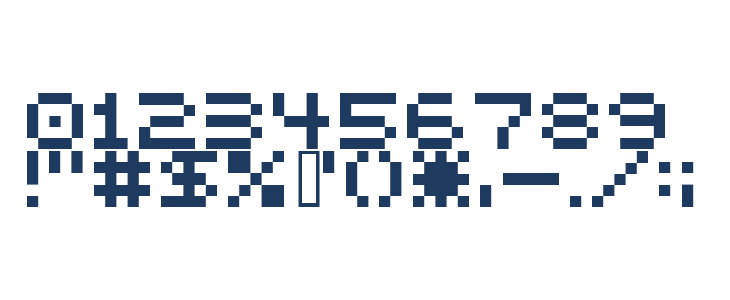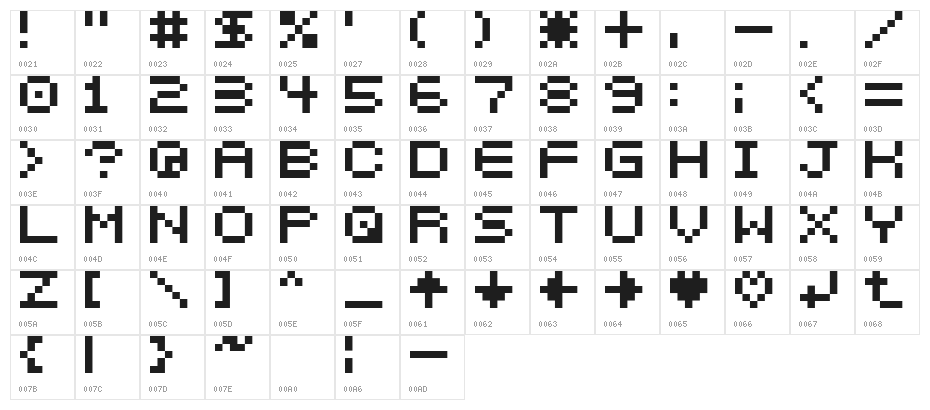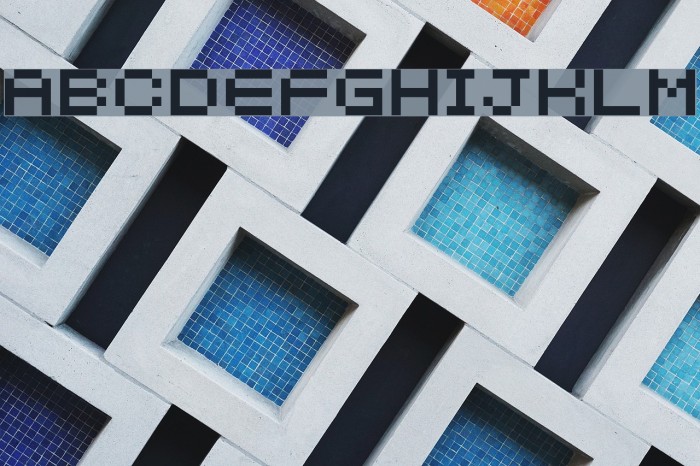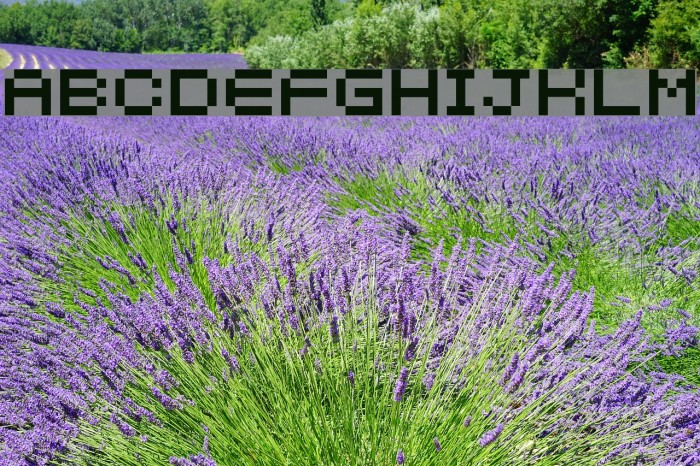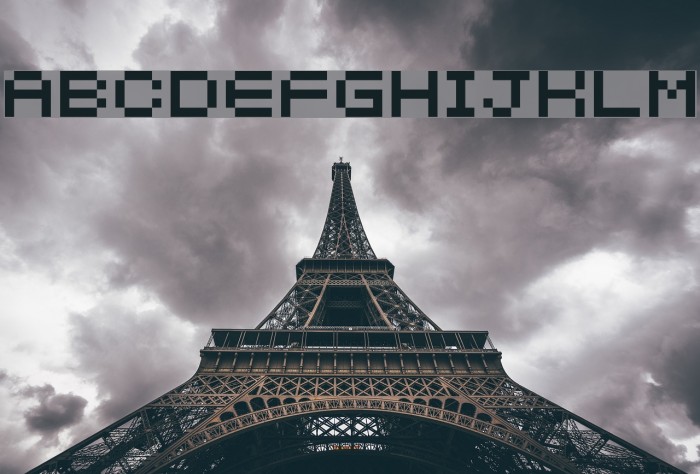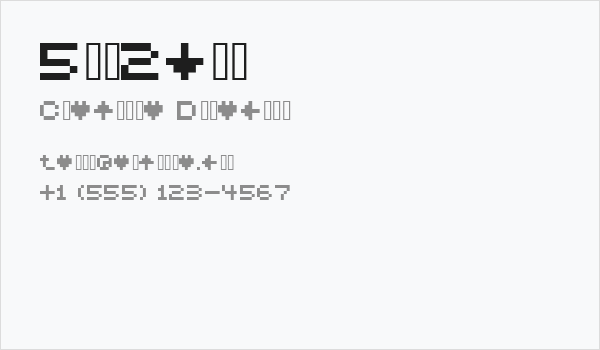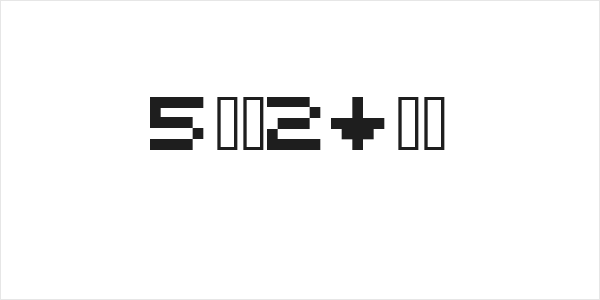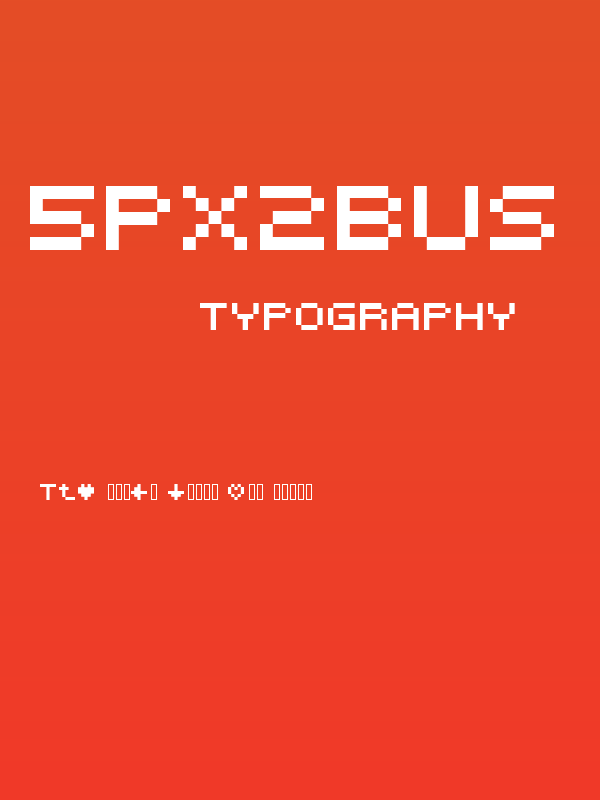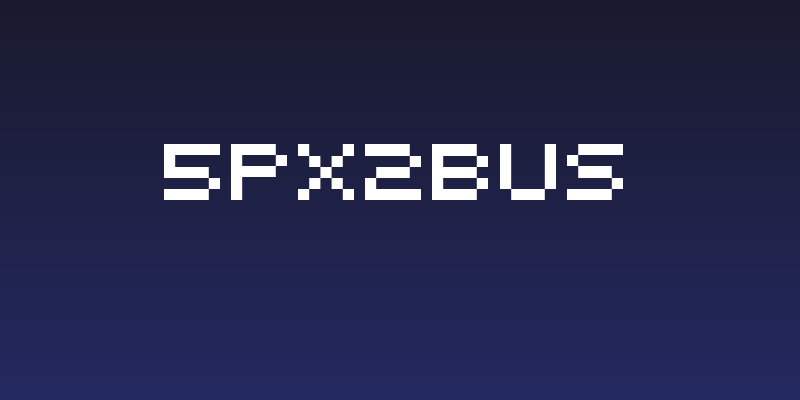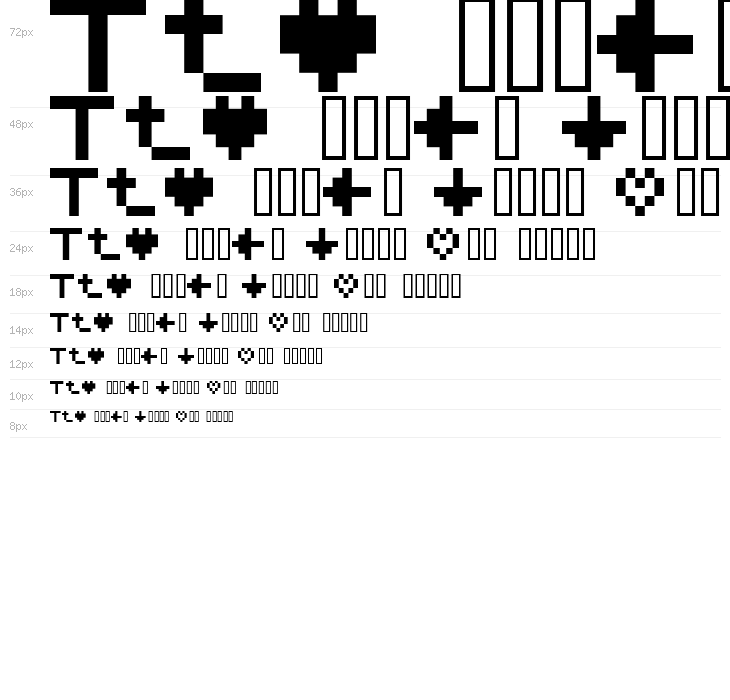
5px2bus Font
| Caso d'uso | Headlines, Logos, Digital Art |
| Progetti proposti | Ideal for retro video game graphics, digital art projects, tech-themed posters, and any design requiring a vintage digital aesthetic. |